Рис. 13. Древнерусское письмо — кириллица.
Азбука выполнена ширококонечными перьями
по мотивам устава XI века.
в греческих и римских эпиграфических
шрифтах.
Современной модификацией антиквы яв¬
ляется ленточная антиква. Она имеет цели¬
ком антиквенные пропорции, соотношение
основных и дополнительных штрихов, но от¬
личается от антиквы отсутствием засечек.
Разнообразия шрифтов этой группы также
можно добиться, изменяя характер начерта¬
ния.
Антиква пером. В последние годы широкое
распространение получили шрифты антик¬
вы, оформленные ширококонечным пером
или плоской кистью. Рукописные формы
этих шрифтов как нельзя лучше подходят
для художественно-оформительских работ,
так как легко воспроизводятся шрифтовыми
инструментами и кистями.
История русского шрифта.
Древнерусское письмо — кириллица.
Древнерусскими называют все рукописные и
первопечатные шрифты со времени возник¬
XVIII века, то есть до образования новой
графики письма и гражданского шрифта.
Создателями славянской азбуки были
братья Кирилл (Константин) и Мефодий,
уроженцы города Солуни (Солоники) в Ма¬
кедонии. Славянский язык был их родным
языком, воспитание и образование они полу¬
чили греческое. В качестве миссионеров-
проповедников братья были посланы в Хаза-
рию, где, как указывает летопись, им дове¬
лось видеть у одного «русина» Евангелие и
Псалтырь, написанные «русьскими письме-
ны». Сведения о том, что славяне до приня¬
тия христианства уже имели какую-то свою
систему письма для гадания и счета «черта¬
Черноризца Храбра — болгарского монаха,
жившего на рубеже IX—X веков. Он же
сообщает, что «черты и резы» были знаками
фигурного письма, и противопоставляет их
«книгам» или буквам, то есть письму фоне¬
тическому. Имевшимся у восточных славян
фигурным письмом, видимо, трудно было
передавать понятия распространявшейся
новой религии — христианства, из-за чего,
по словам Храбра, им приходилось пользо¬
ваться знаками латинскими и греческими
«без устроения», то есть несистематизиро¬
ванной азбукой.
Заслуга Константина (имя Кирилл он
что он впервые создал азбуку с четкой и яс¬
ной графикой букв, положив в основу грече¬
ское унциальное письмо и дополнив ее знака¬
ми, обозначавшими специфические звуки
славянского языка (шипящие, свистящие
и йотированные). Он расставил буквы в
определенной последовательности, придав
им и цифровое значение, которым в течение
многих веков обозначались простые и много¬
значные цифры. Он же с помощью изобре¬
тенной им азбуки сделал первый перевод
Библии на славянский язык. Несмотря на
то, что письмо должно было обслуживать ре¬
алфавита, на основе знания славянской фо¬
нетики и существовавшего уже тогда русско¬
го письма, был явлением прогрессивным,
способствовавшим развитию славянской
культуры и взаимного общения между брат¬
скими народами.
орошему архитектору достаточно листа и карандаша: в быстром эскизе он способен передать объёмы целого комплекса зданий без углубления в детали. Читатель, знакомый со шрифтами Веры Евстафьевой, наверняка согласится, что безупречное чувство формы — одна из ключевых черт её стиля. Кроме того, не забудем про любовь к пишущему инструменту, хотя шрифты Веры не слепо подчиняются суровым законам, диктуемым ширококонечным или остроконечным пером: рукописная практика скорее подпитывает искомые формы букв. И наконец, очевидно пристальное внимание к истории кириллицы, которую Евстафьева рассматривает не как источник украшений «а-ля рюс», но как ключ к естественному «голосу» текста, набранного кириллицей.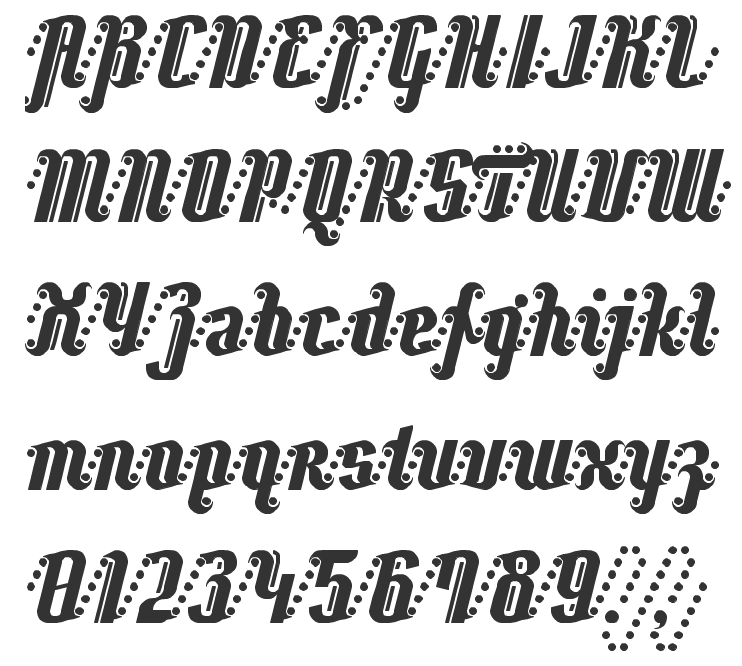
После окончания художественного факультета Московского государственного университета печати в 2003 году Вера Евстафьева отправилась в Королевскую академию искусств в Гааге и стала первым российским студентом знаменитого сегодня факультета Type & Media. Проработав несколько лет дизайнером шрифтового отдела Студии Артемия Лебедева, Вера переключилась на самостоятельную работу и сегодня является независимым дизайнером. Москва, 2013. Фото: Ксения Плотникова.
C чего начался шрифт Амальта?
Давний опыт учёбы у голландских дизайнеров (особенно аналитическая каллиграфия пером и кистью), шрифтовой дизайн, изучение и рассматривание разнообразных исторических материалов и преподавание помогли накопить мне те знания, мысли и побуждения, которые проявились в Амальте.
Не считая студенческих проектов, Амальта — первый некоммерческий шрифт после нескольких сугубо функциональных работ. Он самостоятельно возник из графической идеи, и в первую очередь я решала эстетическую задачу, оставив жёсткие функциональные требования на втором плане — как это и бывает при разработке большинства акцидентных шрифтов.
Во время преподавания в Британской школе дизайна меня увлекло римское капитальное письмо. До этого я в основном писала пером, которое легче поддаётся контролю и жёстко опирается на бумагу. Гибкость же кисти и её свободное положение, парение над листом позволяют легко писать штрихи с вращением либо применять больший и меньший нажим, слегка меняя таким образом толщину штриха, — и формы становятся сложнее, изысканнее. Как доказал Эдвард Катич
Отчасти из-за того, что успех любого нового акцидентного шрифта непредсказуем (мы не говорим об откровенно конъюнктурных под(д)елках), но главным образом потому, что этот шрифт совсем не очевиден для большинства графических дизайнеров, он никуда не «напрашивается», более того — неуверенного в себе типографа он, скорее всего, отпугнёт.